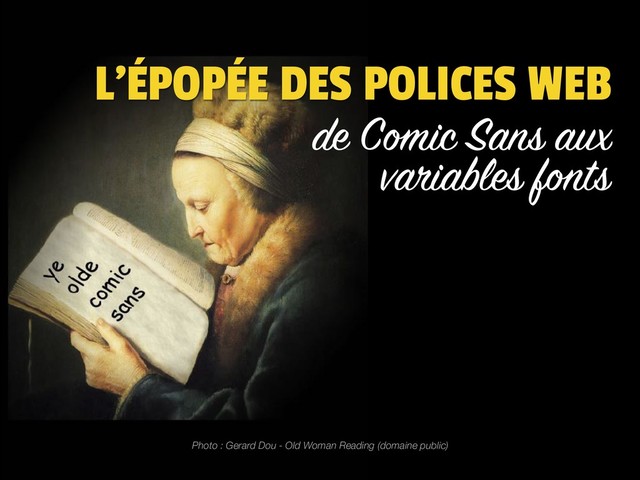
L'épopée des polices web, de Comic Sans aux var...
L'épopée des polices web, de Comic Sans aux variable fonts
On retrace le parcours des polices dans le web, côté CSS. Avec Comic Sans, CSS1, @font-face, les formats de compression, Google Fonts, les fontes d'icônes, les ligatures, font-display et enfin la révolution des variable fonts.
Et il y a de quoi dire !
1. de Comic Sans aux variables fonts L’ÉPOPÉE DES POLICES WEB
2. 1995 Comic Sans 1996 CSS1 1998 @font-face trou noir 2009
woff 2010 Google Fonts 2011 CSS3 2012 Icon Fonts 2013 ligatures 2015 font-display 2016 variable fonts notre parcours…
3. COMIC SANS • Suscite la haine de tous les typographes
• Classée dans les 50 pires inventions du monde
(Times Magazine 2010) • Google lui dédie son 1er Avril 2011 le paradoxe • Favorise la mémorisation des contenus
(étude réalisée à Chesterfield en 2011) • Recommandée en cas de dislexie
4. CSS1 • Né en 1996 grâce à Bert Bos et
Håkon Wium Lie • 53 propriétés (plus de 400 en CSS3) • Beaucoup de propriétés concernant les polices • … Pas toujours intuitives
5. PROPRIÉTÉ 1 « font- », « text- » ou «
autre » ? p { taille de texte: 2em; }
6. PROPRIÉTÉ 2 « font- », « text- » ou «
autre » ? p { graisse de texte: grasse; }
7. PROPRIÉTÉ 3 « font- », « text- » ou «
autre » ? p { couleur de texte: rose; }
8. PROPRIÉTÉ 4 « font- », « text- » ou «
autre » ? p { style de texte: italique; }
9. PROPRIÉTÉ 5 « font- », « text- » ou «
autre » ? p { soulignement de texte: au-dessous; }
10. PROPRIÉTÉ 6 « font- », « text- » ou «
autre » ? p { alignement horizontal de texte: centré; }
11. PROPRIÉTÉ 7 « font- », « text- » ou «
autre » ? p { alignement vertical de texte: centré; }
12. PROPRIÉTÉ 8 « font- », « text- » ou «
autre » ? p { hauteur de ligne de texte: 1.5; }
13. PROPRIÉTÉ 9 « font- », « text- » ou «
autre » ? p { casse du texte: majuscules; }
14. PROPRIÉTÉ 10 « font- », « text- » ou «
autre » ? p { casse du texte: petites majuscules; }
15. @FONT-FACE • Permet d’afficher une police de caractères non présente
chez l’utilisateur(trice) • Existe depuis CSS 2.0 • Pendant longtemps reconnu uniquement par… IE4
via un format propriétaire .eot complexe • Il disparaît donc de CSS 2.0 et réapparaît dans CSS3
10 ans plus tard
16. @font-face { font-family: kiwi; src: url("/fonts/kiwi.ttf"); } on indique son
chemin on nomme la fonte h1 { font-family: kiwi, sans-serif; } on applique la fonte (ici sur <h1>) avec une alternative en cas
de souci
17. @FONT-FACE • sIFR (Scalable Inman Flash Replacement) 3 (JS +
Flash); • typeface.js (JS + SVG/VML); • Cufón (JS + SVG/VML). Une première mini-révolution dans les polices web car
elle rend standard un besoin qui nécessitait auparavant
des bidouilles diverses :
18. .WOFF • En 2009 Web Open Font Format (WOFF 1.0)
proposé par Microsoft, Mozilla et Opera • En 2013, WOFF 2.0
proposé par Google avec une meilleure
compression (brotli vs gzip) et formats compressés
19. .eot embedded open type .ttf
.otf truetype
opentype .svg scalable
vector graphics .woff web open font format .woff2 web open font format 2 9 4 9 4.4 ed WOFF!
20. @font-face { font-family: kiwi;
src:
url("/fonts/kiwi.eot") format("embedded opentype"); url("/fonts/kiwi.eot?#iefix") format("embedded
opentype"), url("/fonts/kiwi.woff2") format("woff2"), url("/fonts/kiwi.woff") format("woff"), url("/fonts/kiwi.ttf") format("truetype"), url("/fonts/kiwi.svg#svgFontName") format("svg"); } « BULLETPROOF (OLD) » syntaxe
21. GOOGLE FONTS • Appelé Google Webfonts avant juin 2013,
puis Google Fonts • 915 familles de polices à ce jour • Toutes les polices sont libres (licence Apache et SIL OFL) • Selon builtwith.com,
42,380,635 sites utilisent Google Font API (2019) • Les 5 polices les plus utilisées : Roboto, Open Sans, Lato,
Montserrat, Roboto condensed
22. GOOGLE FONTS <link href="https:// fonts.googleapis.com/css? family=Roboto" rel="stylesheet"> code HTML proposé
par Google Font (API) div { font-family: Roboto, sans-serif; } CSS pour afficher la police version « import via HTML »
23. GOOGLE FONTS @import url('https:// fonts.googleapis.com/css? family=Roboto'); code CSS proposé
par
Google Font (API) div { font-family: Roboto, sans-serif; } CSS pour afficher la police version « import via CSS »
24. CSS3 • font-variant-numeric
meilleur affichage des nombres • font-smoothing
adoucissement des polices • hyphens
gestion des césures selon la langue • font-kerning
gestion du crénage inter-lettres • etc. mais aussi des trucs bien plus utiles
25. ICON FONTS • Polices de caractères constituées d’icônes • Démocratisées
avec FontAwesome dans Bootstrap • Permet de rassembler des 10aines de pictos en
un seul fichier (« sprite ») • Libres et gratuites : FontAwesome, Iconic, Octicons • Outils de génération : Icomoon, Fontello, Fontastic.
c’est quoi ?
26. @font-face { font-family: MyIconFont; src: url("/fonts/icomoon.ttf"); } on charge la
fonte d’icônes Twitter .icon-twitter::before { font-family: MyIconFont; content: "t"; } on prévoit une classe
pour chaque lettre <i class="icon-twitter"></i> Twitter on applique la fonte d’icônes
27. avantages inconvénients vectoriel 1 seule requête alignements parfois hasardeux nombreux
styles possibles sémantique détournée multicolore impossible accessibilité perfectible ICON FONTS
28. LIGATURES 2013 • Fusion de 2 ou plusieurs graphème…
pour
former un caractère à part entière. • Différentes types de ligatures : ordinaires, esthétiques, historiques, spécifiques. • Doivent être prévues par la police employée. • Quelques polices libres et gratuites : Calendas Plus, Fira Code, Fifita, Raleway, Lobster, Lora, PT Serif, Libre Baskerville,… c’est quoi ?
29. FONT-VARIANT-LIGATURES ligatures courantes font-variant-ligatures: common-ligatures; ligatures historiques font-variant-ligatures: historical-ligatures; adaptation
au contexte et lettres alentour font-variant-ligatures: contextual; ligatures spécifiques proposées par la fonte font-variant-ligatures: discretionary-ligatures;
30. FONT-FEATURE-SETTINGS ligatures courantes (idem que la propriété font-variant-ligature) font-feature-settings: "liga",
"clig ", "dlig", "hlig", "calt"; petites capitales (idem que font-variant: small-caps;) font-feature-settings: "smcp"; propriété opentype « bas niveau » pour cas particuliers ornements calligraphiques (swash) font-feature-settings: "swsh"; ⚠ « swash »≠ « swag »
31. CAS 1 « chargé » ou « pas chargé »
? @font-face { font-family: kiwi;
src: url(kiwi.woff2); } <p>hopla !</p> p { font-family: kiwi; }
32. CAS 2 « chargé » ou « pas chargé »
? @font-face { font-family: kiwi;
src: url(kiwi.woff2); } p { font-family: kiwi; }
33. CAS 2 … sauf sur IE <9 @font-face { font-family:
kiwi;
src: url(kiwi.woff2); } p { font-family: kiwi; } PAS CHARGÉ
34. CAS 3 « chargé » ou « pas chargé »
? @font-face { font-family: kiwi;
src: url(kiwi.woff2); } <p></p> p { font-family: kiwi; }
35. CAS 3 @font-face { font-family: kiwi;
src: url(kiwi.woff2); } …
sauf sur IE <p></p> p { font-family: kiwi; } PAS CHARGÉ
36. CAS 4 « chargé » ou « pas chargé »
? @font-face { font-family: kiwi;
src: url(kiwi.woff2); } <p>hopla !</p> p { font-family: arial, kiwi; } Note : Arial est installé chez l’utilisateur
37. CAS 4 Les specs disent que les navigateurs peuvent charger
le fichier s’ils en ont envie. (pour l’instant, ils ne le font pas) <p>hopla !</p> p { font-family: arial, kiwi; } ÇA DÉPEND @font-face { font-family: kiwi;
src: url(kiwi.woff2); }
38. CAS 5 <p>hopla !</p> « chargé » ou « pas
chargé » ? p { font-family: kiwi; } @media (min-width: 999999px) { @font-face { font-family: kiwi;
src: url(kiwi.woff2); } }
39. CAS 5 <p>hopla !</p> @media (min-width: 999999px) { @font-face {
font-family: kiwi;
src: url(kiwi.woff2); } } p { font-family: kiwi; } … sauf sur IE <11 PAS CHARGÉ
40. CASSIS « chargé » ou « pas chargé » ?
<p>hopla !</p> @font-face { font-family: kiwi;
src: url(kiwi.woff2); } @media (min-width: 99999px) { p { font-family: kiwi; } }
41. CASSIS <p>hopla !</p> @media (min-width: 99999px) { p { font-family:
kiwi; } } PAS CHARGÉ @font-face { font-family: kiwi;
src: url(kiwi.woff2); }
42. FONT-DISPLAY • Propriété CSS liée au chargement des fichiers de
police • Permet d’adopter différentes stratégies de chargement • Un atout considérable pour la performance perçue des
contenus pour la performance
43. HTML CSS fonte 1 fonte 2 400ms 300ms 200ms 100ms
0ms 500ms 600ms 700ms 800ms page blanche ?
44. blocage 1 le rendu du texte est invisible durant cette
phase échange 2 la fonte alternative est affichée durant cette phase échec 3 chargement abandonné, la fonte alternative est affichée ÉTAPES DE RENDU D’UNE FONTE
45. FOIT Flash Of Invisible Text FOUT Flash Of Unstyled Text
FOOT Activité sportive collective autour d’une balle (et où les allemands français gagnent à la fin) (= blocage) (= échange immédiat) COMPORTEMENTS NAVIGATEURS what the FOUT !
46. j’affiche le contenu en open sans " oui open sans
est-il chargé ? blocage
(texte invisible) non échange
(j’affiche sans-serif en attendant) open sans est-il chargé ? non échec
(ça me saoûle, j’affiche sans-serif) open sans est-il chargé ? non oui oui
47. blocage
(texte invisible) échange
(j’affiche sans-serif en attendant) échec
(ça me saoûle, j’affiche sans-serif) • IE = 0s • Chrome, FF, Safari = 3s • Safari (old) = infini blocage selon les navigateurs : • IE = FOUT • Chrome, FF, Safari = FOIT+FOUT • Safari (old) = FOIT traduction :
48. — les spécifications « Les agents utilisateurs décident de leur
stratégie de chargement de fontes (FOUT ou FOIT) tant que le fichier n’est pas chargé »
49. phase de blocage volontaire (= FOIT) font-display: block phase d’échange
immédiate (= FOUT) font-display: swap compromis selon la vitesse de connexion (= le browser peut choisir de ne pas charger la fonte du tout) font-display: optional FONT-DISPLAY valeurs utiles
50. phase de blocage volontaire (= FOIT) font-display: block phase d’échange
immédiate (= FOUT) font-display: swap compromis selon la vitesse de connexion (= le browser peut choisir de ne pas charger la fonte du tout) font-display: optional FONT-DISPLAY icon fonts texte courant valeurs utiles
51. • extension du format de police Open Type, • proposé
par Adobe, Apple, Google et Microsoft (!), • une seule fonte peut contenir de multiples variantes
d’affichage définis par le designer. mais c’est magique !
52. PERSPECTIVES ? • poids et temps de chargement grandement diminués,
• adaptivité à toutes les surfaces et devices, • logos animés ou responsive, • TEXTES MULTICOLORES ! du bon et du moins bon
53. 1995 Comic Sans 1996 CSS1 1998 @font-face trou noir 2009
woff 2010 Google Fonts 2011 CSS3 2012 Icon Fonts 2013 ligatures 2015 font-display 2016 variable fonts L’ÉPOPÉE DES POLICES WEB alors t’as vu, ça a bien bougé, hein ?
54. RÉFÉRENCES • MDN @font-face :
https://developer.mozilla.org/fr/docs/Web/CSS/@font-face • Wikipedia « format